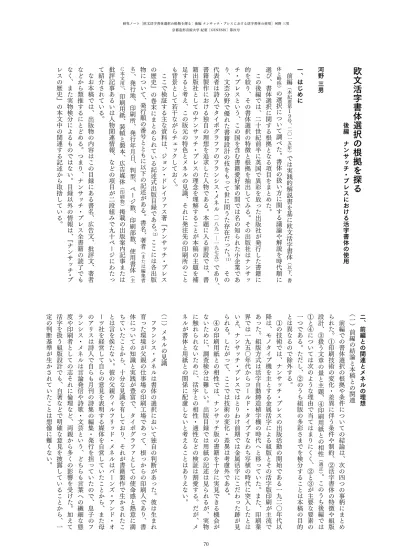
欧文活字書体選択の根拠を探る
後編 ナンサッチ・プレスにおける活字書体の使用 河野 三男 一、はじめに 前 編 ︵ 本 紀 要 第 1 9 号 、 二 〇 一 五 年 ︶ で は 実 践 的 解 説 書 を 基 に 欧 文 活 字 書 体 ︵ 以 下 、 書 体 と 略 称 ︶ の 選 択 に つ い て 調 べ た 。 書 体 の 扱 い 方 に 関 す る 議 論 や 解 説 を 時 代 順 に 選 び 、 書 体 選 択 に 関 す る 根 拠 と な る 項 目 を ま と め た 。 こ の 後 編 で は 、 二 十 世 紀 前 半 に 英 国 で 異 彩 を 放 っ た 出 版 社 が 発 行 し た 書 籍 に 的 を 絞 り 、 そ の 書 体 選 択 の 特 徴 と 根 拠 を 抽 出 し て み る 。 そ の 出 版 社 は ナ ン サ ッ チ ・ プ レ ス と い う 、 こ の 国 を 含 む 書 籍 愛 好 家 の 間 で は 名 の 知 ら れ た 小 企 業 で あ り 、 文 芸 分 野 で 優 れ た 書 籍 設 計 の 技 を も っ て 世 に 問 う た 存 在 だ っ た 。 (1) そ の 代 表 者 は 詩 人 で タ イ ポ グ ラ フ ァ の フ ラ ン シ ス ・ メ ネ ル ︵ 一 八 九 一 ︱ 一 九 七 五 ︶ で あ り 、 書 籍 製 作 に お け る 独 自 の 理 想 を 追 求 し た 人 物 で あ る 。 本 題 に 入 る 前 段 で は 、 書 籍 出 版 社 と し て の ナ ン サ ッ チ ・ プ レ ス の 理 念 を 理 解 す る こ と が 本 稿 の 主 題 を 補 足 す る と 考 え 、 こ の 版 元 の 特 色 と メ ネ ル の 見 識 、 そ れ に 発 注 先 の 印 刷 所 の こ と も 背 景 と し て 若 干 な が ら チ ェ ッ ク し て お く 。 こ こ で 検 証 す る 主 な 資 料 は 、 ジ ョ ン ・ ド レ イ フ ァ ス 著 ﹃ ナ ン サ ッ チ ・ プ レ ス の 歴 史 ﹄ の 巻 末 に ま と め ら れ て い る 記 述 式 出 版 目 録 で あ る 。 (2)こ こ に は 各 出 版 物 に つ い て 、 発 行 順 の 番 号 と と も に 以 下 の 記 述 が あ る 。 書 名 、 著 者 ︵ ま た は 編 集 者 名 ︶ 、 発 行 地 、 印 刷 所 、 発 行 年 月 日 、 判 型 、 ペ ー ジ 数 、 印 刷 部 数 、 使 用 書 体 ︵ 主 に 本 文 用 ︶ 、 印 刷 用 紙 、 装 幀 と 製 本 、 広 告 媒 体 ︵ 印 刷 物 ︶ 掲 載 の 出 版 案 内 記 事 ま た は 批 評 記 事 あ る い は 人 物 関 連 情 報 、 な ど の 項 目 が 二 段 組 み で 九 十 ペ ー ジ に わ た っ て 紹 介 さ れ て い る 。 な お 本 稿 で は 、 出 版 物 の 内 容 は こ の 目 録 に あ る 書 名 、 広 告 文 、 批 評 文 、 著 者 な ど か ら 類 推 す る に と ど め る 。 つ ま り 、 ナ ン サ ッ チ ・ プ レ ス 全 書 籍 の 読 了 で も な く 、 ま た 実 物 検 分 に よ る も の で は な い 。 目 録 以 外 の 情 報 は 、﹃ ナ ン サ ッ チ ・ プ レ ス の 歴 史 ﹄ の 本 文 中 の 関 連 す る 記 述 か ら 取 捨 し て い る 。 二、前編との関連とメネルの理想 ︵ 一 ︶ 前 編 の 結 論 と 本 稿 と の 関 連 前 編 で の 書 体 選 択 の 根 拠 や 条 件 に つ い て の 結 論 は 、 次 の 四 つ の 事 柄 に ま と め ら れ た 。 ① 印 刷 技 術 の 変 化 ・ 差 異 に 伴 う 条 件 や 制 約 、 ② 活 字 書 体 の 特 徴 や 組 版 設 計 、 ③ 扱 う 文 章 の 量 と 主 題 、 ④ 印 刷 用 紙 と の 相 性 ︵ 適 正 ︶ 。 こ の う ち 後 編 で は ① と ④ に つ い て は 次 の よ う な 理 由 で 当 て は ま り に く く 、 ② と ③ が 主 要 な 要 素 の 一 つ で あ る 。 た だ し 、 ② の う ち 組 版 の 多 彩 さ ま で を 検 分 す る こ と は 本 稿 の 目 的 と は 異 な る の で 除 外 す る 。 ① の 技 術 で は 、 ナ ン サ ッ チ ・ プ レ ス の 出 版 活 動 の 開 始 で あ る 一 九 二 〇 年 代 以 降 は 、 モ ノ タ イ プ 機 を 主 と す る 金 属 活 字 に よ る 組 版 と そ の 活 字 版 印 刷 が 主 流 で あ っ た 。 組 版 方 式 は 活 字 自 動 鋳 造 植 字 機 の 時 代 へ と 移 っ て い た 。 ま た 、 印 刷 業 界 で は 一 九 五 〇 年 代 か ら コ ー ル ド ・ タ イ プ す な わ ち 写 植 の 時 代 に 突 入 し た と は い え 、 ナ ン サ ッ チ ・ プ レ ス で は と り わ け 前 期 で は 金 属 活 字 に こ だ わ っ た 跡 が 見 ら れ る 。 し た が っ て 、 こ こ で は 技 術 の 変 化 ・ 差 異 は 考 慮 外 で あ る 。 ④ の 印 刷 用 紙 と の 相 性 で は 、 ナ ン サ ッ チ 版 の 書 籍 を 十 分 に 実 見 で き る 機 会 が な い た め に 、 調 査 検 分 は 難 し い 。 出 版 目 録 で は 用 紙 の 記 述 は 見 ら れ る が 、 実 物 に 触 れ ら れ な い た め に 、 活 字 と の 相 性 ・ 適 性 な ど の 検 証 は 割 愛 す る 。 だ が 、 メ ネ ル が 書 体 と 用 紙 と の 関 係 に 配 慮 し な い と 考 え る こ と は あ り え な い 。 ︵ 二 ︶ メ ネ ル の 見 識 フ ラ ン シ ス ・ メ ネ ル は 書 体 の 選 択 に お い て 独 自 の 判 断 が あ っ た 。 彼 は 生 ま れ 育 っ た 環 境 が 父 親 の 仕 事 場 の 印 刷 工 場 で あ っ て 、 根 っ か ら の 印 刷 人 で あ り 、 書 体 に つ い て の 知 識 と 実 践 が 豊 富 で 、 タ イ ポ グ ラ フ ァ と し て の 使 命 感 と 熱 意 に 満 ち て い た こ と か ら 、 十 分 な 見 識 を 有 し て お り 、 そ れ が 書 籍 製 作 で 生 か さ れ た こ と は 言 を 俟 た な い 。 彼 の 父 親 ウ ィ ル フ リ ッ ド ・ メ ネ ル は バ ー ン ズ ・ ア ン ド ・ オ ー ツ 社 を 経 営 し て 自 ら の 意 見 を 表 明 す る 媒 体 を 自 営 し て い た こ と か ら 、 ま た 母 の ア リ ス は 詩 人 で 自 ら も 月 刊 の 詩 集 の 編 集 ・ 発 行 を 担 っ て い た の で 、 息 子 の フ ラ ン シ ス ・ メ ネ ル は 言 論 発 信 や 詩 歌 ・ 文 芸 と い う 、 ど ち ら も 言 葉 へ の 繊 細 な 態 度 や 印 刷 者 と し て の 志 そ れ に 倫 理 な ど 、 両 親 か ら 多 く の 影 響 を 受 け た 。 加 え て 活 字 を 扱 う 組 版 設 計 で も 、 自 著 な ど で 明 確 な 意 見 を 披 露 し て い る こ と か ら 、 一 定 の 判 断 基 準 が 生 か さ れ て い た こ と は 想 像 に 難 く な い 。示 し て 、 そ れ を 読 み 手 と 共 有 ・ 共 感 し た り 気 づ か せ た り す る 工 夫 で あ る 。 そ こ に こ そ 装 飾 の 意 図 が あ る 、 と メ ネ ル は 考 え て い た 。 そ の 意 味 で 装 飾 は 、 書 き 手 の 意 図 を 妨 げ な い 程 度 に 何 か を 付 加 す る あ る い は 増 幅 す る と い う ﹁ 創 造 的 機 能 性 ﹂ と も 呼 ぶ べ き 配 慮 を 期 待 さ れ て い る 素 材 で も あ っ た 。 読 者 が 模 様 や 図 柄 を 目 に し て 、 紙 面 に 独 特 な 印 象 深 い 表 情 や 心 理 的 な 立 体 感 を 与 え ら れ る 楽 し み と で も 言 え よ う 。 こ の 種 の オ ー ナ メ ン ト 類 の 扱 い 方 に は 組 版 技 術 や 創 造 力 が 必 要 と さ れ 、 そ の パ タ ー ン を 選 ん だ 根 拠 も 試 さ れ る 。 花 形 装 飾 活 字 な ど は 、 そ の 意 味 で タ イ ポ グ ラ フ ァ に と っ て の 腕 の 見 せ ど こ ろ で あ り 、 創 造 性 を か き 立 て ら れ る 素 材 で あ る は ず だ 。 他 方 で ド レ イ フ ァ ス は 、 メ ネ ル が 一 九 二 三 年 に 発 行 し た 活 字 見 本 帳 の 奥 書 か ら 以 下 の よ う な 文 章 を 引 用 し て い る 。 (5) あ る べ き 活 字 と は 、 次 の よ う に 常 識 以 前 の こ と で あ る 。 ① 何 は さ て お き 、 読 み や す い こ と 。 ② 確 か め う る 規 範 、 美 、 ま た は ︵ そ し て ︶ 伝 統 に 従 う こ と 。 ③ で き る だ け 明 瞭 で あ る こ と 。 ④ 印 刷 さ れ た 言 葉 の 意 味 に 対 し て 、 ︵ 活 字 の ︶ 特 色 が ふ さ わ し い こ と 。 ⑤ 飾 り 罫 や 図 版 と 調 和 す る ﹁ 濃 淡 ﹂ で あ る こ と 。 ⑥ 決 め ら れ た 印 刷 工 程 と 決 め ら れ た 紙 に よ っ て 効 果 の あ る 再 生 が 可 能 な こ と 。 ⑦ ︵ 常 識 的 な 心 理 学 の 言 葉 を 使 う と ︶ 読 者 の 心 の 中 で 正 し い 連 想 を 確 立 す る こ と 。 こ こ に メ ネ ル の 書 籍 製 作 に か け る 熱 く か つ 冷 静 な 姿 勢 の 均 衡 の 程 が 十 分 に う か が え る 。 ナ ン サ ッ チ 版 の 書 籍 の 全 て が こ の よ う な 理 想 を 具 現 し て い る か ど う か は 定 か で は な い が 、 少 な く と も そ の 意 気 込 み と 質 の 維 持 に 懸 命 で あ っ た と 想 像 で き る 。 同 社 の 設 立 に 際 し て ﹁ 中 身 の 重 要 性 、 体 裁 の 美 し さ 、 適 正 な 定 価 と い う 三 つ の 理 想 に 従 っ て 中 身 を 選 ん で 製 作 す る こ と に あ る ﹂ と い う 確 固 た る 意 志 が 、 一 九 二 三 年 の 設 立 直 後 の 出 版 案 内 の 中 で 表 明 さ れ て い る 。 (6) な お 、 日 本 で は こ の 時 期 に す で に 一 人 の 詩 人 が ナ ン サ ッ チ ・ プ レ ス に 注 目 し て い た 。﹃ 游 牧 記 ﹄ を 残 し た 夭 折 の 詩 人 ・ 平 井 功 が メ ネ ル に 手 紙 を 送 り 、 そ の 書 籍 製 作 に つ い て 質 問 し て い た と 聞 い て い る 。 日 夏 耿 之 介 や 庄 司 泉 水 ら の 愛 書 家 彼 に よ る 書 籍 製 作 に 対 す る 態 度 は 、 そ の 著 ﹃ イ ギ リ ス の 印 刷 本 ﹄ (3)と ジ ョ ン ・ ド レ イ フ ァ ス 著 ﹃ ナ ン サ ッ チ ・ プ レ ス の 歴 史 ﹄ (4)に 詳 し い 。 以 下 の 彼 の 言 葉 か ら そ の 真 摯 な 姿 勢 や 理 想 と す る 実 践 方 針 を 見 て み る 。 ﹁ 可 読 性 と は 、 十 分 に 油 が 注 が れ た ベ ア リ ン グ の こ と で 、 意 味 と い う 車 輪 を ギ ー ギ ー と 音 を 立 て ず に 回 転 さ せ る も の だ ﹂ ﹁ 言 葉 に つ い て の 様 々 な 表 し 方 が 可 能 な 限 り あ る 。著 者 の 言 葉 を 肉 体 化 す る こ と だ ﹂ ﹁ 書 物 の 物 理 的 な 心 臓 や 頭 部 は 、 印 刷 さ れ た ペ ー ジ に あ る ﹂ ﹁ 我 々 の 役 に 立 ち 、 我 々 を 救 う の は 、 活 字 で あ る ﹂ ﹁ ︵ 新 聞 の ︶ 印 刷 は 偉 大 な 記 録 者 だ 。 書 類 は 残 り 続 け 、 そ の 証 拠 は い つ で も 入 手 で き て 、 記 事 は 歴 史 と な る 。 証 拠 を 隠 す こ と は 難 し い し 、 印 刷 は 究 極 の 言 葉 を 有 す る こ と に 至 る 。 つ ま り 鉛 で で き た 二 十 六 の 兵 士 で 、 私 は 世 界 を 征 服 し た と ﹂ ﹁ 書 物 は 分 か り や す く あ る べ き で 、 書 き 手 の 目 的 へ の 誠 実 な 奉 仕 で あ る ﹂ ﹁ 書 物 は 読 ま れ る だ け の も の で は な く 、 尊 重 ・ 評 価 さ れ る べ き で も あ る 。 言 い 換 え れ ば 、 書 物 は 分 か り や す く あ る べ き で 、 書 き 手 の 目 的 ・ 意 図 へ の 誠 実 な 奉 仕 で あ る 。 ま た 、 読 み や す い こ と が 必 要 だ 。 時 と し て 書 き 手 の 意 図 を 増 幅 し た り 、 あ る い は そ れ 自 体 の 不 可 欠 な 形 態 へ と 接 近 す る な ど だ ﹂ ﹁ さ さ や か な が ら も 印 刷 と い う 男 勝 り の 三 つ の 女 神 を 眺 め て み よ う 。そ れ は 分 か り や す さ 、 読 み や す さ 、 そ し て 装 飾 だ ﹂ ﹁ 理 想 を 言 え ば 、 文 章 の 一 行 は 八 か ら 十 一 単 語 で あ る べ き だ ろ う ﹂ ﹁ 派 手 に 着 飾 っ た 書 物 で は な く 、 絶 妙 に し て 的 確 に 、 出 し ゃ ば る こ と な く 書 物 へ の 思 い で 身 を ま と っ た 書 物 を 欲 し て い る の だ ﹂ こ こ に 引 用 し た ﹁ 男 勝 り の 女 神 ﹂ の 三 番 目 の 装 飾 は 、 ナ ン サ ッ チ ・ プ レ ス の 特 徴 の 一 つ で あ る ﹁ 隠 喩 に 富 ん だ 印 刷 (a llu siv e p rin tin g) ﹂ を 理 解 す る に は 好 例 で あ る 。 こ の 言 葉 は メ ネ ル が 尊 敬 す る ア メ リ カ 人 ブ ル ー ス ・ ロ ジ ャ ー ズ ︵ 一 八 七 〇 ︱ 一 九 五 七 ︶ が 既 に 唱 え て い た 。 こ の 隠 喩 と は 書 籍 製 作 全 般 の デ ザ イ ン つ ま り 装 幀 、 製 本 材 料 、 扉 な ど と 、 書 体 選 択 で も 発 揮 さ れ る 。 例 え ば 装 飾 と は た だ 眼 を ひ く も の で も や た ら に 飾 り 立 て る こ と で も な く 、 メ ッ セ ー ジ の 内 容 や 背 景 を 暗
で き る 記 述 が あ り 、 ナ ン サ ッ チ 社 内 で 印 刷 さ れ た か 同 族 関 係 の 印 刷 工 場 に よ る も の と 思 わ れ る が 特 定 で き ず 、 実 態 が 曖 昧 で あ る と い う 理 由 に よ る 。 業 者 名 の 内 訳 は 、 ウ ィ リ ア ム ・ ブ レ ド ン ・ ア ン ド ・ サ ン 社 が 二 十 二 点 、 R ・ R ク ラ ー ク 社 が 十 九 点 、 ウ ィ リ ア ム ・ ク ロ ウ ズ ・ ア ン ド ・ サ ン ズ 社 が 十 四 点 、 ロ バ ー ト ・ マ ク レ ホ ウ ズ 社 が 十 三 点 、 キ ー ノ ッ ク ・ プ レ ス が 十 二 点 、 オ ッ ク ス フ ォ ー ド 大 学 印 刷 局 が 十 一 点 、 ケ ン ブ リ ッ ジ 大 学 印 刷 局 と フ ァ ン フ ェ ア ・ プ レ ス が 各 十 点 、 ヘ リ テ ィ ッ ジ ・ プ レ ス と 私 的 印 刷 所 が 各 九 点 で あ る 。 海 外 発 注 は ア メ リ カ と フ ラ ン ス に あ り 、 前 者 は ヘ リ テ ィ ッ ジ ・ プ レ ス と 、 ク ィ ン ・ ア ン ド ・ ボ ー デ ン 社 、 レ オ ・ ハ ー ト 社 で 、 後 者 は プ ロ タ 印 刷 社 で あ る 。 次 に こ れ ら の 印 刷 所 が 受 注 し た 書 体 の 特 徴 を 眺 め て み る 。ウ ィ リ ア ム ・ ブ レ ド ン ・ ア ン ド ・ サ ン 社 は キ ャ ズ ロ ン 書 体 と プ ラ ン タ ン 書 体 で の 組 版 と 印 刷 を 主 に 受 注 し て お り 、 そ の 他 に 四 書 体 の 使 用 が 記 録 さ れ て い る R ・ R ク ラ ー ク 社 は ス コ ッ チ ・ ロ ー マ ン 書 体 と バ ス カ ヴ ィ ル 書 体 そ れ に タ イ ム ズ ・ N ・ R 書 体 の 使 用 が 多 い 。 ウ ィ リ ア ム ・ ク ロ ウ ズ ・ ア ン ド ・ サ ン ズ 社 は モ ノ タ イ プ 社 と 関 係 が 強 く 、 メ ネ ル か ら 七 書 体 の 仕 事 を 受 注 し 、 ナ ン サ ッ チ 版 プ ラ ン タ ン 書 体 と い う 特 注 書 体 の 使 用 が 四 点 あ る 。 ロ バ ー ト ・ マ ク レ ホ ウ ズ 社 は 七 書 体 を 指 定 さ れ 、 タ イ ム ズ ・ N ・ R 書 体 が も っ と も 多 い 。 キ ー ノ ッ ク ・ プ レ ス は 六 書 体 で の 印 刷 を 受 注 し 、 モ ノ タ イ プ 社 版 ギ ャ ラ モ ン 書 体 ︵ ジ ャ ノ ン 系 で 、 ギ ャ ラ モ ン 書 体 の 模 倣 の 復 刻 版 ︶ と ベ ン ボ 書 体 で の 組 版 受 注 が 際 立 つ 。 オ ッ ク ス フ ォ ー ド 大 学 印 刷 局 は 十 一 点 で 三 書 体 の 使 用 を 受 注 し 、 そ の 内 で 同 印 刷 局 が 歴 史 的 遺 産 と し て 所 有 す る 十 七 世 紀 前 半 の フ ェ ル 書 体 の 母 型 か ら 鋳 込 ん だ 活 字 を 七 点 で 使 用 し た 。 ケ ン ブ リ ッ ジ 大 学 印 刷 局 は 九 書 体 で 十 点 を 印 刷 し て い る し 、 フ ァ ン フ ェ ア ・ プ レ ス に は 特 徴 あ る 書 体 は み ら れ な い が 、 ガ ウ デ ィ ・ モ ダ ン 書 体 が 目 を 引 く 。 ア メ リ カ の 印 刷 所 で あ る ヘ リ テ ィ ッ ジ ・ プ レ ス は 特 に 多 く 使 用 し て い る 書 体 は な く 八 書 体 で あ る が 、 一 書 体 で 明 記 が な い 。 私 的 印 刷 所 は ジ ャ ン ソ ン 書 体 で 半 分 の 四 点 を 印 刷 し て い る 。 フ ラ ン ス の プ ロ タ 社 で は コ シ ャ ン と フ ー ル ニ エ の 二 書 体 で の 印 刷 を 受 注 し 、 ク ィ ン ・ ア ン ド ・ ボ ー デ ン 社 と レ オ ・ ハ ー ト 社 で 合 わ せ て 四 点 を 印 刷 し 、 全 て コ シ ャ ン 書 体 で 印 刷 し て い る 。 両 書 体 は フ ラ ン ス 生 ま れ で 、 そ の 復 刻 版 活 字 で あ る 。 こ れ ら 以 外 で 我 々 に 馴 染 み の あ る 印 刷 所 を あ げ て お く 。 オ リ ヴ ァ ・ サ イ モ ン が 携 わ っ て い た カ ー ウ ェ ン ・ プ レ ス 、 オ ラ ン ダ の ハ ー グ に あ っ た ヨ ハ ネ ス ・ エ た ち が 平 井 に ナ ン サ ッ チ 版 の 魅 力 に つ い て 教 え た と み ら れ る 。 平 井 に は 組 版 へ の 意 欲 的 な 挑 戦 に 応 え う る 印 刷 所 の 選 択 な ど に 関 し て 、 困 難 や 悩 み が あ っ た か ら と 伝 え ら れ て い る 。 そ し て ド レ イ フ ァ ス は 活 字 の 機 能 に 関 す る 、 次 の よ う な メ ネ ル の 言 及 を 紹 介 し て い る 。 文 字 の プ ロ ポ ー シ ョ ン に お い て 美 し さ に ﹁ 純 粋 な ﹂ 基 準 と い う も の が あ る と い う 考 え に 傾 い た が 、 そ の 種 の 美 し さ の 代 わ り と な る 最 も 有 効 で 実 証 で き る も の が あ る 場 合 に は 、 殊 の 外 難 し く て 疑 い が あ る こ と に 四 苦 八 苦 す る 必 要 は な い 。 こ れ は 用 の 美 ︵ bea uty of util ity ︶ と い う 見 解 で あ っ て 、伝 統 と 慣 習 へ の 尊 重 で も あ る 。 ︵ 略 ︶ 印 圧 の 鋭 さ ・ 明 快 さ 、 曲 線 と 結 合 部 、 極 微 で の 正 確 さ と 安 定 感 、 目 の 歪 み ︵ 人 の 目 は 実 測 上 の 中 央 を 下 に 見 る し 、 こ れ は 知 ら れ て い る ︶ へ の 考 慮 、 文 字 が 満 足 の ゆ く よ う に つ な が り 、 語 を 形 成 し 、 文 字 が 示 さ れ た と き の 媒 体 の た め の 感 覚 ︱ ︱ 金 属 、 石 、 イ ン ク ︱ ︱ そ れ と そ れ を 作 っ た 道 具 へ の 配 慮 、 あ の 活 字 こ れ ら の す べ て が 技 術 上 の 完 璧 な 現 れ で あ り 、 現 段 階 で 美 の 定 義 で あ る か ど う か の 判 断 の た め の 実 際 上 の 試 し と な る の で あ る 。 (7) ﹁ 用 の 美 ﹂ あ る い は ﹁ 用 と 美 ﹂ と は 、我 が 国 で 柳 宗 悦 が 唱 え た 民 芸 運 動 で の キ ー ワ ー ド の 一 つ で あ る が 、 そ の 契 機 は 十 九 ︱ 二 十 世 紀 の イ ギ リ ス で 起 き た ア ー ツ ・ ア ン ド ・ ク ラ フ ツ 運 動 に あ っ た 。 メ ネ ル も そ の 時 代 の 空 気 を 十 分 に 吸 っ て い た こ と と 無 関 係 で は あ り え な い 。 た だ し 、 工 芸 作 家 W ・ モ リ ス が 辿 り 着 い た 書 籍 製 作 の 態 度 は 、 タ イ ポ グ ラ フ ィ の 理 解 の 深 さ に お い て メ ネ ル に は 及 ば な い 。 書 き 手 へ の 寄 り 添 い 方 や 意 識 が モ リ ス に は 弱 い こ と で そ の 結 果 は ア ー ト に 傾 き 、 逆 に メ ネ ル は 真 の デ ザ イ ン に 没 入 で き た 。 ︵ 三 ︶ 発 注 先 の 印 刷 所 ナ ン サ ッ チ ・ プ レ ス か ら 印 刷 を 受 注 し た 企 業 に つ い て 見 て み る 。 明 記 さ れ て い る 社 名 の 総 計 は 三 十 六 社 ほ ど あ り 、 受 注 し た 点 数 か ら み て 上 位 十 社 だ け で 百 二 十 九 点 を 印 刷 し て い る 。 こ れ は 全 体 の 七 十 % ほ ど に あ た る 。 受 注 印 刷 所 を ﹁ 三 十 六 社 ほ ど ﹂ と し た が 、こ れ は ﹁ 私 的 に 印 刷 ﹂ と い う 自 社 内 で の 作 業 を 推 測
た 事 実 を 報 告 し て い る 。 (8)こ れ は プ ラ ン タ ン 書 体 の こ と を 指 し て い る 。 ま た 、 ラ イ ノ タ イ プ 社 版 の バ ス カ ヴ ィ ル 、 ス コ ッ チ ・ ロ ー マ ン 、 グ ラ ン ジ ョ ン 、 ギ ャ ラ モ ン な ど の 一 部 の 書 体 や 、 手 組 み 用 の ジ ャ ン ソ ン な ど も 選 ば れ て い る 。 と り わ け ジ ャ ン ソ ン 書 体 は 十 二 点 で 使 用 さ れ 、 そ の う ち 手 組 み 用 七 点 、 ラ イ ノ タ イ プ 社 版 が 三 点 、 不 明 が 二 点 と 、 手 組 み 用 に ナ ン サ ッ チ 版 と し て 修 正 文 字 種 を 含 む 書 体 が 使 用 さ れ て い る 。 ︵ 二 ︶ 使 用 書 体 の 数 メ ネ ル お よ び 彼 の 後 継 者 が 書 籍 な ら び に 小 冊 子 で 選 ん だ 本 文 用 書 体 の 一 覧 は 表 1 に 示 す 通 り で あ る 。 全 発 行 書 名 数 一 九 四 で 、 記 載 不 明 を 含 め て 三 十 一 種 類 の 書 体 が 使 用 さ れ た が 、 書 名 数 は 一 四 二 点 で 、 シ リ ー ズ で あ る が 異 な る 内 容 で あ れ ば 一 点 と 数 え た 。同 一 書 名 で 複 数 書 体 の 混 植 と 書 体 名 の 不 明 が あ る た め に 、書 名 数 よ り も 多 く な っ て い る 。 主 要 選 択 書 体 に つ い て は 、 上 位 十 書 体 で 百 三 十 二 点 を 組 ん で お り 、 そ の 割 合 は 六 十 八 % で 七 割 近 い 。 ち な み に 上 位 五 位 ま で の 六 書 体 で 、 全 体 の 五 割 を 超 え て い る 。 こ の 場 合 、 本 稿 の 基 に な る 文 献 で あ る ド レ イ フ ァ ス 著 ﹃ ナ ン サ ッ チ ・ プ レ ス の 歴 史 ﹄ も 同 じ ナ ン サ ッ チ 発 行 で あ る が 、 そ こ に 使 用 さ れ て い る 活 字 の バ ル ブ 書 体 は こ の リ ス ト か ら 除 外 し て い る 。 ま た 、 表 一 の 使 用 書 体 の う ち 使 用 開 始 年 と 活 字 製 造 年 に 注 目 す る と 、 興 味 あ る こ と が 見 ら れ る 。 バ ル マ ー 書 体 は 製 造 と 同 年 に 、 ギ ャ ラ モ ン 書 体 と グ ラ ン ジ ョ ン 書 体 は 翌 年 に 、 バ ス カ ヴ ィ ル 書 体 と ベ ン ボ 書 体 と ガ ウ デ ィ 書 体 は 二 年 後 に 、 そ れ ぞ れ 使 用 さ れ て い る 。 メ ネ ル が い か に 新 し い 書 体 の 出 現 に 敏 感 だ っ た か を 物 語 る 。 こ れ ら か ら ラ イ ノ タ イ プ 版 グ ラ ン ジ ョ ン 書 体 を 除 く 五 書 体 は 、 全 て モ ノ タ イ プ 社 版 で あ る 。 ち な み に 製 造 後 三 年 で の 使 用 は ポ リ フ ィ ラ ス 書 体 と そ の イ タ リ ッ ク 体 の 別 名 ブ ラ ド ー 書 体 で あ る 。 ン ス ヘ デ 社 、 キ ャ ズ ロ ン 書 体 を 復 活 さ せ た ウ ィ テ ィ ン ガ ム 運 営 の チ ジ ッ ク ︵ チ ズ ウ ィ ッ ク ︶ ・ プ レ ス な ど が あ る 。 活 字 書 体 と そ の 組 版 の 要 望 に 応 え う る 印 刷 所 が 指 定 さ れ て い た と 考 え ら れ る こ と か ら 、 希 望 書 体 を 備 え て い る 印 刷 所 を 選 ん で の 発 注 だ ろ う 。 本 文 の 組 版 と 印 刷 を 分 け て 発 注 し た こ と も あ る の で 、 印 刷 所 が 全 て 先 に あ げ た 書 体 を 備 え て 組 ん で い た の で は な い こ と に 留 意 が 必 要 で あ る が 、 そ の 方 法 は こ こ で は 省 く 。 ナ ン サ ッ チ ・ プ レ ス は 出 版 業 社 で あ り 、 メ ネ ル は 主 に 編 集 と デ ザ イ ン を 担 当 し て い た 。 彼 が 活 躍 し た 期 間 は 第 二 次 大 戦 の 前 ま で で 、 そ の 後 は ア メ リ カ 人 に 経 営 が 委 ね ら れ た 。 そ の 歴 史 の 前 半 の 運 営 と 書 籍 製 作 の 主 体 は メ ネ ル で あ り 、 そ の 意 志 は 助 言 な ど で そ の 後 の 経 営 陣 に 継 続 さ れ た と は い え 、 実 際 の 書 籍 デ ザ イ ン は 変 わ ら ざ る を 得 な か っ た だ ろ う 。 そ れ に し て も 、 ナ ン サ ッ チ と い う 名 称 を 普 及 さ せ た 功 績 は メ ネ ル の デ ザ イ ン 的 感 性 と 文 学 お よ び タ イ ポ グ ラ フ ィ の 才 能 ・ 知 識 に あ る こ と は 疑 い な い 。 さ ら に 人 的 交 流 の 広 さ も あ り 、 そ の 条 件 か ら 生 み 出 さ れ た 書 籍 の 外 部 と 内 部 の 質 の 高 さ や 豊 か さ は 、 並 び の な い 光 彩 を 放 っ て 人 気 を 得 て い る 。 以 上 の こ と を 念 頭 に 、 次 に ナ ン サ ッ チ ・ プ レ ス の 書 体 使 用 状 況 の 全 体 像 を 概 観 し て み る 。 三、使用書体の特徴と概略 ︵ 一 ︶ 活 字 の 供 給 ナ ン サ ッ チ が 書 籍 本 文 の 組 版 ・ 印 刷 を 外 注 し た 時 代 は 、 二 十 世 紀 前 半 の 半 世 紀 ほ ど ︵ 一 九 二 三 ︱ 一 九 六 八 年 ︶ の 期 間 で あ る 。 そ れ は モ ノ タ イ プ 式 と ラ イ ノ タ イ プ 式 の 自 動 鋳 造 植 字 機 に よ る 金 属 活 字 で の 機 械 組 版 が 全 盛 を 誇 っ て い た 時 代 で あ る 。 さ ら に 、 ナ ン サ ッ チ が 選 択 し た 書 体 は ス タ ン リ ー ・ モ リ ス ン ︵ 一 八 八 九 ︱ 一 九 六 七 ︶ と の 関 係 を 無 視 で き な い 。 モ リ ス ン は メ ネ ル の 若 い 頃 か ら の 友 人 で あ り 、 当 時 モ ノ タ イ プ 社 で 活 字 書 体 復 刻 計 画 の 指 揮 を 執 っ て い た 。 メ ネ ル が 選 ん だ 書 体 の 大 多 数 が モ ノ タ イ プ 社 製 の 活 字 で あ っ た こ と か ら 、 相 互 の 理 解 と 友 情 が 友 好 裏 に 働 い た こ と が 伝 わ っ て い る 。 例 え ば ジ ョ ン ・ ド レ イ フ ァ ス は ﹁ モ リ ス ン の 存 在 に よ り ラ ン ス ト ン ・ モ ノ タ イ プ 社 か ら ︵ ナ ン サ ッ チ へ ︱ 引 用 者 ︶ の 特 殊 な 文 字 種 の 調 達 が 容 易 に な っ た ﹂ と し て 、 下 図 に 見 ら れ る よ う に 大 文 字 を 低 く さ せ た り ア セ ン ダ ー や デ ィ セ ン ダ ー を 長 く さ せ た り す る な ど の 工 夫 が 要 請 さ れ プランタン書体の比較: 同じ文字で左がナンサッチ版、右がモノタイプ版。
順位 書体名 使用数 割合(%) 使用期間(年) 活字製造年* MT外の製造 供給所名 製造所(MT) 1 キャズロン(Caslon) 26 13.40 1923 – 38 1916 (13) ? (13) 2 プランタン(Plantin) 19 9.79 1923 – 55 1913 (19) 3 ギャラモン(Garamond) 16 8.25 1923 – 53 1922 (10) 1924 (2) LT 1917 (4) ATF
4 タイムズ(Times New Roman.) 15 7.73 1939 – 53 1932 (13) 1932 (2) LT?
5 バスカヴィル(Baskerville) 12 6.19 1925 – 39 1923 (10) 1923 (2) LT ジャンソン(Janson) 12 6.19 1926 – 39 1937 (3) LT 1919 (9) Stempel 6 スコッチ・ローマン(Scotch R.) 10 5.15 1925 – 35 1920 (8) ? (2) ? 7 コシャン(Cochin) 8 4.12 1931 – 44 1923 (8) 8 ベンボ(Bembo) 7 3.61 1931 – 64 1929 (7) フェル(Fell) 7 3.61 1923 – 37 1672 (7) OUP 小 計 132 68.04 88 44 9 ボドニ(Bodoni) 6 3.09 1926 – 36 1922 (5) ? (1) ? 10 エアハルト(Ehrhardt) 5 2.58 1950 – 68 1937 (5) フールニエ(Fournier) 5 2.58 1929 – 63 1925 (5) パペチュア(Perpetua) 5 2.58 1936 – 51 1929 (5) 11 ガウディ・モダン(Goudy Mod.) 4 2.06 1930 – 53 1928 (4) ポリフィラス(Poliphilus) 4 2.06 1926 – 33 1923 (2) ? (2) ?
12 ブラド(Blado = Poliphilus italic) 3 1.54 1926 – 28 1923 (2) ? (1) ?
グランジョン(Granjon) 3 1.54 1932 – 39 1928–31 (3) LT インプリント(Imprint) 3 1.54 1932 – 56 1912 (3) ワルバウム(Walbaum) 3 1.54 1926 – 39 1933 (1) 1919 (2) Berthold 13 バルマー(Bulmer) 2 1.03 1937 – 45 1937 (1) 1928 (1) ATF セントール(Centaur) 2 1.03 1934 – 56 1929 (1) 1929 (1) LT ダンテ(Dante) 2 1.03 1965 – 68 1957 (2) フライシュマン(Fleischmann) 2 1.03 1928 – 34 1929 (2) Enschede 14 ベル(Bell) 1 0.52 1936 1930 (1)
アリギ(Arrighi = Centaur italic) 1 0.52 1934 1929 (1)
カレドニア(Caledonia) 1 0.52 1945 1938 (1) ルテシャ(Lutetia) 1 0.52 1934 1925 (1) Enschede ノイラント(Neuland) 1 0.52 1924 1923 (1) K'spore ロムルス(Romulus) 1 0.52 1954 1931 (1) Enschede ファン・ダイク(Van Dijck) 1 0.52 1928 1935 (1) 小 計 56 28.87 40 16 不明書体 6 3.09 6 鋳造所別小計 128 66 30書体の使用合計数 194 100.00 表 1: 本文主要書体の一覧 * ()内は使用数。特に明記ない場合は、MT(モノタイプ社)を表す。 ** LTはライノタイプ社、AF Tはアメリカ活字鋳造会社、BTはベルトルド社、Sはシュテンペル社、Bはバウアー社。 活字製造年は製造完了年か発売年かにより、1年程度の差異がある。
キャズロン、Caslon プランタン、MT Plantin ギャラモン、MT Garamond コシャン、Cochin ジャンソン、Stempel Janson スコッチ・ローマン、Scotch Roman
タイムズ・ニュー・ローマン、MT Times New Roman フェル、Oxford Fell
バスカヴィル、MT Baskerville ベンボ、MT Bembo
︵ 三 ︶ 使 用 書 体 の 傾 向 ︱ 著 者 ・ ジ ャ ン ル と の 関 連 以 下 で は 発 行 書 籍 全 体 の 七 割 近 く を 占 め る 上 位 十 書 体 に つ い て 、 表 2 と 表 3 を 基 に 探 る 。 表 2 は 著 者 の 生 没 年 代 と ジ ャ ン ル と の 関 連 、 表 3 は 著 者 に つ い て の 判 明 し う る 専 門 分 野 と 特 徴 を 、 そ れ ぞ れ 書 体 別 に ま と め た 。 そ こ か ら 以 下 の 項 目 に つ い て 書 体 選 択 の 傾 向 を 探 る 。 ① 著 者 の 生 没 年 代 ︵ 表 2 参 照 ︶ 、 ② 著 者 の 専 門 分 野 ・ 特 徴 ︵ 表 3 参 照 ︶ 、 ③ ジ ャ ン ル ︵ 表 2 参 照 ︶ 、 ④ 特 徴 的 傾 向 の ま と め 、 の 四 項 目 で あ る 。 な お 、 ジ ャ ン ル に つ い て は カ タ ロ グ 解 説 文 と 書 名 を 参 考 に し つ つ 、 さ ら に 筆 者 が 可 能 な 限 り 調 べ て 判 断 し た 。 個 々 の 内 容 の 背 景 と な る 年 代 に 関 し て こ の カ タ ロ グ か ら 判 断 す る こ と は 、 記 述 で 不 明 が あ り 徹 底 し て い な い た め に 不 可 能 で あ る 。 そ の よ う に 年 代 と ジ ャ ン ル で は 不 明 を 含 む 場 合 が あ る の で 、 表 2 で は 別 途 で 不 明 の 欄 を 設 け て 示 し た 。 表2-8: コシャン書体 ジャンル 著者・内容の年代(世紀) 古 代 17-18 18-19 19-20 不 明 計 戯曲/歌謡/詩歌 1 1 小説/物語 1 1 小説(フランス) 1 4 1 6 小計 1 1 1 4 1 8 表2-7: スコッチ・ローマン書体 ジャンル 著者・内容の年代(世紀) 16 17-18 18-19 19-20 不 明 計 戯曲/歌謡/詩歌 1 1 小説/物語 1 1 随筆・小論/評論 1 2 3 2 8 小計 1 1 2 4 2 10 表2-9: ベンボ書体 ジャンル 著者・内容の年代(世紀) 16-17 18-19 19-20 不 明 計 戯曲/歌謡/詩歌 2 2 小説/物語 1 2 3 随筆・小論/評論 2 2 小計 2 1 4 7 表2-10: フェル書体 ジャンル 著者・内容の年代(世紀) 16-17 17-18 不 明 計 戯曲/歌謡/詩歌 2 2 随筆・小論/評論 1 1 宗教/哲学 1 1 2 その他/不明 1 1 2 小計 5 1 1 7 表2-3: ギャラモン書体 ジャンル 著者・内容の年代(世紀) 古 代 16 - 17 18 - 19 19 - 20 不 明 計 戯曲/歌謡/詩歌 1 3 1 5 小説/物語 1 2 3 1 7 宗教/哲学 1 1 2 その他/不明 1 1 2 小計 4 4 2 5 1 16 表2-6: ジャンソン書体 ジャンル 著者・内容の年代(世紀) 17-18 19-20 不 明 計 戯曲/歌謡/詩歌 1 2 2 5 随筆・小論/評論 1 2 1 4 小説/物語 1 1 その他/不明 1 1 2 小計 3 6 3 12 表2-5: バスカヴィル書体 ジャンル 著者・内容の年代(世紀) 16-17 17-18 18-19 19-20 不 明 計 戯曲/歌謡/詩歌 1 1 3 1 6 小説/物語 1 1 2 随筆/評論 1 1 2 4 小計 1 1 4 2 4 12 表2-4: タイムズ・ニュー・ローマン書体 ジャンル 著者・内容の年代(世紀) 17-18 18-19 19-20 不 明 計 戯曲/歌謡/詩歌 1 3 2 6 小説/物語 1 1 2 自然科学 1 1 随筆・小論/評論 1 1 1 2 5 その他/不明 1 1 小計 2 4 5 4 15 表2-1: キャズロン書体 ジャンル 著者・内容の年代(世紀) 古 代 16-17 17-18 18-19 19-20 不 明 計 戯曲/歌謡/詩歌 1 5 1 3 10 小説/物語 1 1 1 1 4 随筆/評論 2 2 4 宗教 1 1 その他/不明 1 3 3 7 小計 1 2 6 5 9 3 26 表2-2: プランタン書体 ジャンル 著者・内容の年代(世紀) 古 代 16-17 18-19 19-20 不 明 計 戯曲/歌謡/詩歌 1 9 10 小説/物語 1 1 2 随筆・小論/評論 1 1 2 宗教 2 2 その他/不明 1 2 3 小計 3 1 1 13 1 19 表2: 書体別、著者とジャンル(使用数上位10書体)
表3-1:キャズロン書体(18−20世紀)
番 号 著者名または書名中の人物名 著者の分野 特 徴
10 ハドスン(W. H. Hadson, 1841︲1922) 植物学者 自然主義
27・45・85 B・ダーウィン(B. Darwin, 1871︲1954) 絵本作家・挿絵画家 児童文学
E・ダーウィン(E. Darwin, 1876︲1961) 絵本作家・挿絵画家 児童文学
36 b ターナー(Walter Turner, 1889︲1946) 詩人・小説家 評論 43・103 ブレイク(W. Blake, 1757︲1827) 詩人・画家 幻想的・浪漫主義 46・88 レイヴァー(J. Laver, 1806︲1872) 小説家 音楽的・絵画的 48 ヴォルテール(Voltaire, 1694︲1778) 小説家・思想家 啓蒙的合理主義 66 ファルクハー(G. Farquhar, ?) 劇作家 喜劇的 67 アリス・メネル(A. Meynell, 1847︲1922) 詩人(フランシスの母親) 易しい言葉遣い 68 ローレンス(D. H. Lawrence, 1885︲1930) 絵本作家 神秘的唯物論 表3-4:タイムズ・N・ローマン書体(18−20世紀) 番 号 著者名または書名中の人物名 著者の分野 特 徴 15g・116 a・b メネル(F. Meynell, 1891︲1975) 詩人・編集者・出版人 社会主義者 94 コウルリッジ(S. T. Colerridge, 1772︲1834) 詩人 浪漫主義 98 コリアー(J. Collier, 1901︲1980) 小説家 悪魔 106 シモンズ(A. J. A. Symons, 1900-1941) 伝記作家 愛書家 フラワー(D. Flower, 1907– ?) 伝記作家 愛書家 メネル(F. Meynell, 1891︲1975) 詩人・編集者・出版人 社会主義者 111 ホイットマン(W. Whitman, 1819︲1892) アメリカの詩人 自由詩・政治的 114 ホワイト(G. White, 1720︲1793) 博物学 流麗な文体 117 バイロン(Byron, 1788︲1824) 詩人 政治的・風刺的 118 シェリー(Shelly, 1792︲1822) 詩人 浪漫派・無神論 表3-5:バスカヴィル書体と関連人物(17−19世紀) 番 号 著者名または書名中の人物名 著者の分野 特 徴 24 ブレイク(W. Blake, 1757–1827) 詩人・画家 幻想的・浪漫主義 26 ペロル(Perrault, 1628–1703) 詩人・小説家 童話も有名 41 コベット(W. Cobbette, 1763–1835) ジャーナリスト 論争家 90 コウルリッジ(S. T. Colerridge, 1772–1834) 詩人 幻想・神秘的・浪漫派 92 モリス(W. Morris, 1834–1896) 工芸作家・印刷者 社会主義者 表3-2:プランタン書体(19−20世紀) 番 号 著者名または書名中の人物名 著者の分野 特 徴 8・30 トラー(E. Toller, 1893︲1939) 劇作家 反ナチ、左翼 15 a-f・123(編集)メネル(F. Meynell, 1891︲1975) 詩人・編集者・出版人 社会主義者
85 B・ダーウィン(Bernard & Darwin, 1871︲1954) 絵本作家・挿絵画家 児童文学
E・ダーウィン(Elenor Darwin, 1876︲1961) 絵本作家・挿絵画家 児童文学
131 スティヴンスン(R. L. Stevenson, 1850︲1894) 詩人・小説家 旅行作家 133 ラング(A. Lang, 1844︲1912) 民俗学者 お伽話の収集 表3: 書体別、著者専門分野・特徴 (表中の番号とは、カタログの書名番号を示す) 表3-3:ギャラモン書体(古代と19−20世紀) 番 号 著者名または書名中の人物名 著者の分野 特 徴 2 メレディス(G. Meredith, 1828︲1909) 小説家・詩人・評論家 メネルの両親の友人 7 アプレイウス(L. Apuleius, 前2世紀) 作家(ギリシャ) 伝奇小説 12 アナクレオン(Anacreon, 前6世紀) 詩人(ギリシャ) 酒と恋・抒情 63 プルターク(Plutarch, 2世紀) 哲学者(ギリシャ) 博識 16・31 ムーア(G. Moore, 1852︲1933) 小説家 自然主義 19 プラトン(Plato, 前4世紀) 哲学者(ギリシャ) 霊魂不滅・イディア論 107 d ハドスン(W. H. Hudson, 1841︲1922) 植物学者 自然主義 115 キャロル(L. Caroll, 1832︲1898) 小説家・数学者 風刺・幻想的 117 a バルザック(H. Balzac, 1799︲1850) 小説家(フランス) リアリズム文学
表3-6:ジャンソン書体(16−20世紀)
番 号 著者名または書名中の人物名 著者の分野 特 徴
36a メネル(F. Meynell, 1891–1975) 詩人・編集者・出版人 社会主義者
44 ハーバート(G. Herbert, 1593–1633) 聖職者・詩人 形而上派
55a メネル(E. Meynell, 1882–1926) 作家・古書店主 フランシスの兄
65 フォンテネル(B. de Fontenell, ) 思想家・啓蒙家 宗教批判
65a, 68a メネル(F. Meynell, 1891–1975) 詩人・編集者・出版人 社会主義者
82 エヴリン(J. Evelyn, 1620–1706) 日記作家 ? 107c ハウズマン(A. Housman, 1859–1936) 詩人・ラテン語学者 古典・ロマン主義 114 a ストーン(I. Stone, 1903–1989) 伝記作家 ? 表3-8:コシャン書体(18−20世紀) 番 号 著者名または書名中の人物名 著者の分野 特 徴 72 ホーマー(J. Homer, 前8世紀) 詩人(ギリシャ) 吟遊詩人 105 コウルリッジ(S. T. Colerridge, 1772–1834) 詩人(ロマン派) 幻想・神秘的 115c ヴォルテール(Voltaire, 1694–1778) 小説家(仏) 風刺・啓蒙合理 115f フランス(A. France, 1844–1924) 小説家(仏) 批評的 115g モーパッサン(G. Mopassant, 1850–1893) 小説家(仏) 自然主義 115h ゾラ(E. Zola, 1840–1902) 小説家(仏) 自然主義・幻想的 表3-9:ベンボ書体(16−20世紀) 番 号 著者名または書名中の人物名 著者の分野 特 徴 73 シドニー(P. Sydney, 1554–1586) 詩人 ソネット形式 107b シェイクスピア(W. Shakespeare, 1564–1616) 劇作家・詩人 警句・名句・新語
117a バルザック(O. Balzac, 1799–1850) 小説家(仏) リアリズム
128 メネル(F. Meynell, 1891–1975) 詩人・編集者・出版人 社会主義者 132 マクドナルド(G. MacDonald, 1824–1905) 児童文学者・詩人 ? 136 ネスビット(E. Nesbit, 1858–1924) 童話作家 ? 表3-10:フェル書体(16−18世紀) 番 号 著者名または書名中の人物名 著者の分野 特 徴 1・6・71・86 ダン(J. Donne, 1572–1631) 詩人 官能的恋愛詩 37 エヴリン(J. Evelyn, 1620–1706) 日記作家 警句・名句・新語 109 ミルトン(J. Milton, 1608–1674) 詩人 宗教的・幻想的 100(編集)オールト(A. Ault, 1880–1950) ポープの研究者 ? 表3-7:スコッチ・ローマン書体と関連人物(18−20世紀) 番 号 著者名または書名中の人物名 著者の分野 特 徴 52 コンラッド(J. Conrad, 1857–1924) 小説家(ポーランド) ? 64 オースティン(J. Austin, 1775–1817) 小説家 写実主義 71a ディケンズ(C. Dickens, 1812–1870) 詩人 諧謔的 75 ハズリット(W. Hazlitt, ?–1930) 詩人・随筆家 浪漫主義 キーンズ(G. Keynes, ?) ? 114b メレコヴスキー(Merejcoveski, 1866–1941) 詩人・小説家(ロシア) 歴史小説
十 六 世 紀 フ ラ ン ス を 代 表 す る 世 界 的 に 有 名 な ギ ャ ラ モ ン 設 計 の 活 字 ま た は そ れ を 模 倣 し た 十 七 世 紀 の 活 字 を モ デ ル に 、 十 九 世 紀 末 か ら 二 十 世 紀 初 頭 に 欧 米 各 国 の 活 字 鋳 造 所 か ら 供 給 さ れ た 。 ① 十 九 ︱ 二 十 世 紀 と 十 六 ︱ 十 七 世 紀 、 そ れ に 古 代 の 著 者 が 目 立 つ 。 ② 九 人 の 著 者 の う ち 、 ギ リ シ ャ 人 四 名 と フ ラ ン ス 人 の 一 名 、 計 五 名 が 外 国 人 著 者 。 古 代 ギ リ シ ャ の 小 説 や 思 想 を 内 容 と す る も の が 目 立 つ が 、 伝 奇 小 説 、 叙 情 的 、 風 刺 的 、 自 然 主 義 、 リ ア リ ズ ム な ど 多 様 な ジ ャ ン ル 。 ③ 小 説 ・ 物 語 と 詩 歌 ・ 韻 文 ・ 戯 曲 に 多 い 。 ④ ギ ャ ラ モ ン 書 体 誕 生 の 世 紀 と の 一 致 が あ る の は 四 点 。 ギ リ シ ャ 時 代 の 著 者 が 多 め で 、 ギ リ シ ャ 時 代 と 十 六 世 紀 と 二 十 世 紀 の ﹁ 著 者 の 年 代 ﹂ そ れ に 多 岐 に わ た る ﹁ ジ ャ ン ル ﹂ が 特 徴 。 ■ タ イ ム ズ ・ ニ ュ ー ・ ロ ー マ ン 書 体 一 九 三 二 年 に 日 刊 新 聞 用 に 特 化 し て 設 計 さ れ た 書 体 。 黒 み が や や 強 く 硬 質 な テ ク ス チ ュ ア を 印 象 づ け る 書 体 で あ る た め に 、 客 観 的 な テ キ ス ト で あ る 理 工 系 の 内 容 や 言 論 ・ 批 評 ・ ビ ジ ネ ス の 分 野 に 多 く 選 ば れ て い る 。 ① 十 九 ︱ 二 十 世 紀 が 目 立 つ 。 ② 詩 人 ・ 小 説 家 が 多 く 、 そ の 他 に は 学 者 が い て 、 近 代 の 著 作 に 集 中 。 出 版 人 で あ り 編 集 者 で も あ る メ ネ ル 自 身 が ま と め て い る も の が 三 点 。 ③ 詩 歌 ・ 韻 文 と 小 論 ・ 評 論 に 集 中 。 詩 歌 関 連 で は 意 外 な 印 象 。 社 会 主 義 や 無 神 論 な ど の 思 想 性 が 背 景 に あ る よ う な 傾 向 。 ④ 随 筆 ・ 評 論 に つ い て は 、 現 在 で も ジ ャ ー ナ リ ス テ ィ ッ ク で 客 観 性 を 標 榜 す る 内 容 が 濃 厚 で あ る こ と か ら も 納 得 で き る 。 詩 歌 で の 使 用 は 、 こ の 書 体 の 明 快 さ と 詩 歌 へ の 過 剰 な 感 情 的 思 い 入 れ を 意 識 的 に 抑 制 し て い る か 、あ る い は 挑 戦 的 試 み か 、興 味 深 い 選 択 。﹁ 著 者 の 年 代 ﹂﹁ 著 者 の 特 徴 ﹂ ﹁ 著 作 の ジ ャ ン ル ﹂ が 平 均 的 な 要 素 。 ■ バ ス カ ヴ ィ ル 書 体 十 八 世 紀 中 頃 に 出 現 し た 書 体 の 復 刻 版 。こ こ で は モ ノ タ イ プ 社 版 が 十 点 、ラ イ ノ タ イ プ 社 版 が 二 点 で 使 用 さ れ て い る 。 後 者 の 方 が オ リ ジ ナ ル に 忠 実 だ が 、 弱 々 し く 印 象 が 芳 し く な い 。 ① 十 八 ︱ 十 九 世 紀 が 多 い 。 ② 詩 人 が や や 多 い が 、 ジ ャ ー ナ リ ス ト で 政 治 評 論 家 の コ ベ ッ ト も い る 。 浪 ■ キ ャ ズ ロ ン 書 体 十 八 世 紀 前 半 に 生 ま れ た イ ギ リ ス を 代 表 す る 書 体 で 、 全 二 十 六 点 に 使 用 。 ① 十 六 か ら 十 九 世 紀 ま で に も 散 在 す る が 、 十 七 か ら 二 十 世 紀 の 著 者 に 集 中 傾 向 。 ② 詩 人 、 小 説 家 、 劇 作 家 、 植 物 学 者 、 絵 本 作 家 ︵ 画 家 ︶ に 分 け ら れ る 。 ヴ ォ ル テ ー ル だ け が フ ラ ン ス 人 。 自 然 主 義 、 浪 漫 主 義 ま た は 幻 想 的 、 神 秘 主 義 的 、 音 楽 的 ま た は 絵 画 的 、 喜 劇 的 な 内 容 を 得 意 と す る 人 物 な ど と 変 化 に 富 む 。 重 複 を 含 め て 画 家 が 六 点 を 占 め る 。 ③ 戯 曲 ・ 歌 謡 ・ 詩 歌 が 目 立 つ が 、 小 説 ・ 物 語 や 随 筆 ・ 評 論 も 多 い 。 特 徴 で は 児 童 文 学 が 顕 著 。 ④ キ ャ ズ ロ ン 書 体 誕 生 の 年 代 は 十 八 世 紀 前 半 で あ る の で 、 著 者 の 年 代 と 傾 向 の 一 致 は 見 ら れ な い 。 む し ろ ﹁ 著 者 の 分 野 と そ の 特 徴 ﹂ か ら 選 ば れ て い る 。 強 い 癖 が 少 な い こ と か ら 一 般 的 に 万 能 的 な 書 体 と し て 選 ば れ る が 、 こ こ で は 哲 学 ・ 宗 教 ・ 社 会 的 思 想 な ど と は 縁 遠 い よ う に 思 え る 。 こ れ は 特 徴 的 な 選 択 。 ■ プ ラ ン タ ン 書 体 一 九 一 三 年 に イ ギ リ ス の モ ノ タ イ プ 社 工 場 長 ピ ア ポ ン の 主 導 で 、 十 六 世 紀 ベ ル ギ ー の プ ラ ン タ ン 印 刷 所 の 活 字 見 本 帳 掲 載 の R ・ グ ラ ン ジ ョ ン の 活 字 を モ デ ル に 設 計 さ れ た と さ れ る や や 骨 太 の 穏 や か な 書 体 。 ① 十 九 ︱ 二 十 世 紀 に 多 い 。 ② 劇 作 家 、 絵 本 作 家 、 詩 人 ・ 小 説 家 、 民 俗 学 者 に 区 分 。 著 者 に は ド イ ツ 人 の ト ラ ー が い る 。 古 き の ど か な 時 代 を 彷 彿 と さ せ る 作 家 が 目 立 つ し 、 そ れ が 暗 に 現 代 社 会 へ の 批 判 と し て 垣 間 見 ら れ る 内 容 か 。 主 張 の 強 さ を 秘 め る 作 品 が 多 い 。 ③ 詩 歌 ・ 韻 文 ・ 歌 謡 に 集 中 。 古 代 で は 随 筆 ・ 宗 教 関 連 で も 選 ば れ て い る 。 十 二 点 の う ち 七 点 は Th e w eek -en d b oo kと い う 小 冊 子 で あ り 、 田 舎 で 働 く 人 々 が 週 末 に 読 む こ と を 想 定 し た 社 交 的 な 歌 謡 集 ま た は 詩 文 集 。 歌 や ゲ ー ム を 主 と し た 生 活 感 あ ふ れ る 趣 味 的 な 内 容 。 ④ ﹁ジ ャ ン ル ﹂ の 特 徴 が 関 係 。 十 六 世 紀 の 著 者 の 書 名 で は 一 つ 使 わ れ て い る だ け で あ る こ と か ら 、 年 代 に 根 拠 が あ っ て の 選 択 で は な い 。 ■ ギ ャ ラ モ ン 書 体
■ ベ ン ボ 書 体 十 五 世 紀 末 の ヴ ェ ネ チ ア で ア ル ド ︵ ア ル ダ ス ︶ が 使 っ た 最 初 の オ ー ル ド ・ ロ ー マ ン 体 の 復 刻 版 。 二 百 五 十 年 ほ ど の 間 に 影 響 を 及 ぼ し 、 復 刻 版 は 二 十 世 紀 の 書 籍 に 多 く 使 わ れ た 人 気 あ る 書 体 。 ① 十 九 ︱ 二 十 世 紀 が 多 め 。 ② 詩 人 、 劇 作 家 、 小 説 家 、 童 話 作 家 な ど で 、 警 句 ・ 批 評 や リ ア リ ズ ム を 得 意 と す る 著 者 。 ③ 小 説 ・ 物 語 、 詩 歌 ・ 歌 謡 、 小 論 ・ 評 論 と ま ん べ ん な く 選 択 。 ④ 万 能 的 な 書 体 で も あ る が 、 私 的 批 評 と い う ﹁ 著 者 の 特 徴 ﹂ と 関 連 。 ■ フ ェ ル 書 体 十 七 世 紀 に オ ッ ク ス フ ォ ー ド 大 学 の 教 授 だ っ た フ ェ ル 博 士 が フ ァ ン ・ ダ イ ク 設 計 の 活 字 を は じ め と す る オ ラ ン ダ の 活 字 を 調 べ て 設 計 さ せ た 書 体 の 復 刻 版 。 ① 十 六 ︱ 十 七 世 紀 に 集 中 。 ② 詩 人 と 日 記 作 家 で 、 個 人 色 が 強 く 現 れ る 内 容 か 。 ③ 詩 歌 ・ 歌 謡 、 小 論 ・ 評 論 、 宗 教 ・ 哲 学 に も 使 用 。 ④ 十 七 世 紀 と い う 清 教 徒 革 命 か ら 王 政 復 古 、 国 教 統 一 な ど と 宗 教 問 題 が 吹 き ま く っ た 時 代 の 著 者 た ち と 合 致 。 つ ま り 、﹁ 著 者 の 年 代 ﹂ と ﹁ ジ ャ ン ル ﹂ と の 関 係 が 際 立 つ 。 ︵ 四 ︶ 使 用 主 要 書 体 の 傾 向 ︱ ま と め 右 に 調 べ た 十 書 体 の 選 択 要 素 と 傾 向 を 点 数 化 し て 以 下 に ま と め て み る 。 傾 向 が 最 も 強 い 場 合 を 五 点 、 傾 向 が や や 見 ら れ る 場 合 を 三 点 、 最 も 弱 い 場 合 を 一 点 と 設 定 し た 。 書体名 著者の年代 著者の分野・特徴 著作のジャンル キャズロン 1 3 3 プランタン 5 3 3 ギャラモン 5 1 3 タイムズ・N・ローマン 3 3 3 バスカヴィル 3 1 3 ジャンソン 3 3 3 スコッチ・ローマン 3 1 5 漫 主 義 派 が 二 名 で 、 社 会 主 義 者 の モ リ ス も い て 、 や や 古 き 英 国 へ の 郷 愁 が 滲 む 。 ③ 詩 歌 ・ 歌 謡 と 小 論 ・ 評 論 に 集 中 。 ④ 英 国 人 気 質 が 思 い 起 こ さ れ る よ う な 内 容 が 集 ま っ て い る の か 。 書 体 誕 生 の 時 代 と 一 致 。﹁ 著 者 の 年 代 ﹂ と ﹁ 著 作 の ジ ャ ン ル ﹂ が 影 響 。 ■ ジ ャ ン ソ ン 書 体 ハ ン ガ リ ー 人 ニ コ ラ ・ キ シ ュ が 十 七 世 紀 に 設 計 し た 書 体 の 復 刻 版 。 こ れ は 誤 っ て ア ン ト ン ・ ジ ャ ン ソ ン の 活 字 だ と さ れ た 書 体 だ と 、 ハ リ ー ・ カ ー タ ー ら が 明 ら か に し た 。 (9) ① 十 九 ︱ 二 十 世 紀 が 多 く て 全 体 の 半 数 で あ る 。 十 七 世 紀 の 著 作 に も 三 点 が 選 ば れ て い る 。 ② 聖 職 者 、 詩 人 、 思 想 家 、 学 者 、 作 家 。 特 徴 は 古 典 主 義 者 や 社 会 主 義 者 ま た は 宗 教 批 判 者 な ど 。 ③ 詩 歌 ・ 歌 謡 と 小 論 . 評 論 に 集 中 。 ④ ﹁著 者 の 年 代 ﹂﹁ 著 者 の 分 野 ・ 特 徴 ﹂﹁ ジ ャ ン ル ﹂ の 要 素 が 強 い 。 ■ ス コ ッ チ ・ ロ ー マ ン 書 体 十 八 世 紀 後 半 の ス コ ッ ト ラ ン ド で 作 ら れ た 書 体 が 十 九 世 紀 に ア メ リ カ に 渡 っ て こ の 名 称 を 得 た 書 体 。 イ ギ リ ス 製 の 活 字 で は 珍 し く モ ダ ン ・ ロ ー マ ン に 分 類 。 ① 十 九 ︱ 二 十 世 紀 が 多 い 。 ② 詩 人 と 小 説 家 で 占 め ら れ 、 異 国 人 著 者 が 二 名 。 歴 史 的 ・ 浪 漫 主 義 的 傾 向 を 帯 び た 著 者 。 ③ 小 論 ・ 評 論 に 圧 倒 的 に 集 中 。 ④ ﹁著 作 の ジ ャ ン ル ﹂ で 一 定 の 傾 向 が 強 く 、﹁ 著 者 の 年 代 ﹂ と も 重 な る 。 ■ コ シ ャ ン 書 体 十 八 世 紀 フ ラ ン ス で 挿 絵 画 家 で あ っ た コ シ ャ ン が 設 計 し た 書 体 の 復 刻 版 。 エ ッ ク ス ハ イ ト が 低 く 、 上 品 で 異 色 の 書 体 で あ る 。 ① 十 八 ︱ 二 十 世 紀 が 多 い 。 ② フ ラ ン ス の 小 説 家 に 集 中 。 幻 想 的 、 風 刺 的 し た が っ て 批 評 的 、 神 秘 的 な 内 容 を 得 意 と す る 著 者 が 多 い 。 ③ 主 に フ ラ ン ス の 恋 愛 小 説 で 使 用 。 ④ ﹁著 者 の 年 代 ﹂ と ﹁ 著 作 の ジ ャ ン ル ﹂ に 深 く 関 わ る 選 択 。
以 上 の こ と か ら 、 メ ネ ル の 書 体 選 択 の 根 拠 に は 常 に 著 者 の 存 在 が 中 心 に あ る こ と が 確 認 で き る 。 数 字 で 見 る と 、﹁ 著 者 の 年 代 ﹂﹁ 著 作 の ジ ャ ン ル ﹂ が 核 と な り 、 そ れ に ﹁ 著 者 の 分 野 ・ 特 徴 ﹂ が 結 び つ い て い る 様 相 を 呈 す る 。 こ の こ と は 、 メ ネ ル の 言 動 と 重 な る 。 つ ま り 、﹁ 著 者 の 言 葉 を 肉 体 化 す る こ と ﹂﹁ 書 き 手 の 目 的 へ の 誠 実 な 奉 仕 で あ る ﹂﹁ 書 き 手 の 意 図 を 増 幅 し た り ﹂ と い う 、著 者 の 存 在 こ そ が 書 体 選 択 の 核 で あ る と の 考 え 方 が 実 際 面 で 反 映 し て い る 。 コシャン 3 1 5 ベンボ 3 1 1 フェル 5 1 1 合計点 34 18 30 ジャンル 著者の年代(数字は世紀を表す) 書体名 戯曲/歌謡/詩歌 古 代 16−17 17−18 18−19 19−20 不 明 小 計 合 計 キャズロン 1 5 1 3 10 プランタン 1 9 10 ギャラモン 1 3 1 5 タイムズ・N・R 1 3 2 6 バスカヴィル 1 1 3 1 1 7 ジャンソン 1 2 2 5 スコッチ・R 1 1 コシャン 1 1 ベンボ 2 2 フェル 2 2 49 小説/物語 古 代 16−17 17−18 18−19 19−20 不 明 小 計 キャズロン 1 1 1 1 4 プランタン 1 1 2 ギャラモン 1 2 3 1 7 タイムズ・N・R 1 1 2 バスカヴィル 1 1 2 ジャンソン 1 1 スコッチ・R 1 1 コシャン 1 1 4 1 7 ベンボ 1 2 3 フェル 0 29 随筆/評論 古 代 16−17 17−18 18−19 19−20 不 明 小 計 キャズロン 2 2 4 プランタン 1 1 2 ギャラモン 0 タイムズ・N・R 1 1 1 2 5 バスカヴィル 1 2 1 4 ジャンソン 1 2 1 4 スコッチ・R 1 2 3 2 8 コシャン 0 ベンボ 2 2 フェル 1 1 30 宗教/哲学 古 代 16−17 17−18 18−19 19−20 不 明 小 計 キャズロン 1 1 プランタン 2 2 ギャラモン 1 1 2 タイムズ・N・R 0 バスカヴィル 0 ジャンソン 0 スコッチ・R 0 コシャン 0 ベンボ 0 フェル 1 1 2 7 その他(不明含む) 古 代 16−17 17−18 18−19 19−20 不 明 小 計 キャズロン 1 3 3 7 プランタン 1 2 3 ギャラモン 1 1 2 タイムズ・N・R 1 1 バスカヴィル 0 ジャンソン 1 1 2 スコッチ・R 0 コシャン 0 ベンボ 0 フェル 1 1 2 17 合 計 9 16 15 20 54 18 132 割 合(%) 6.8 12.1 11.4 15.2 40.9 13.6 100 表4: ジャンルと時代別にみる書体の使用(使用数上位10書体)
イ ク 設 計 ダ ン テ 書 体 で は 十 五 世 紀 末 の イ タ リ ア に あ る し 、 ベ ル 書 体 は 十 八 世 紀 イ ギ リ ス の R ・ オ ー ス テ ィ ン 、 バ ル マ ー 書 体 は 同 W ・ マ ー テ ィ ン が 設 計 し た 書 体 を モ デ ル と し 、 ア メ リ カ 人 ド ゥ イ ギ ン ズ 設 計 の カ レ ド ニ ア 書 体 は 十 八 世 紀 の オ ー ス テ ィ ン の 影 響 が 濃 い 。 そ し て 、 フ ラ イ シ ュ マ ン 書 体 は 十 八 世 紀 の オ ラ ン ダ の 活 字 設 計 者 の 書 体 を 下 敷 き に し て お り 、 ル テ シ ャ 書 体 と ロ ム ル ス 書 体 の モ デ ル は 不 明 で 、 ル ド ル フ ・ コ ッ ホ 設 計 の ノ イ ラ ン ト 書 体 は 独 創 的 書 体 で モ デ ル は な い 。 し た が っ て 、 こ れ ら の 書 体 が 著 者 の 年 代 で 十 九 ︱ 二 十 世 紀 に 多 い こ と と は 無 関 係 で あ る と 言 え る 。 ② の ジ ャ ン ル に つ い て は 、 書 名 と 著 作 の 内 容 そ の 他 の 要 素 が 関 係 し て い る と 推 測 で き る 書 体 が 見 ら れ る 。 そ れ が 詩 歌 ・ 随 筆 で あ る こ と か ら 、 こ こ に は メ ネ ル の 主 観 も 影 を 落 と し や す い だ ろ う 。 以 下 で チ ェ ッ ク し て み る 。 セ ン ト ー ル 書 体 と ア リ ギ 書 体 は 、H ・ エ リ ス の 著 作 で は 解 説 的 な 批 評 的 小 論 で 選 ば れ て い る 。 エ リ ス 自 身 は 十 九 か ら 二 十 世 紀 に か け て 生 き た 精 神 分 析 学 者 で 、 性 心 理 学 を 専 門 と し て い た 。 カ タ ロ グ 中 に は 、 こ の 企 画 の 目 的 の 一 つ は ﹁ 一 人 の 詩 人 へ の 関 心 を 再 び 呼 び 起 こ す こ と で あ り 、こ の 詩 人 ︵ チ ャ プ マ ン ︱ 引 用 者 ︶ と ジ ョ ン ・ ダ ン と の 相 性 の 良 さ が 現 代 の 詩 的 興 趣 の 中 で 共 感 の 響 き 合 い を 見 出 し た 方 が 良 い と 願 っ て い る ﹂ と 、販 売 促 進 用 見 本 パ ン フ レ ッ ト の 広 告 文 に あ る 。 (10)つ ま り 、 著 者 と 内 容 に 沿 っ た 書 体 選 択 と 言 え る 。 同 じ く セ ン ト ー ル 書 体 を 選 ん だ の は 、 W ・ C ・ マ ル キ ス 著 の 手 紙 と 詩 に お い て で あ る 。 マ ル キ ス は 十 七 世 紀 の 法 律 家 で あ り 詩 人 で も あ っ た 。 こ こ で の 選 択 の 理 由 は 記 述 が 極 め て 少 な く 、 不 明 で あ る 。 イ タ リ ア の 活 字 を モ デ ル に し た ダ ン テ 書 体 は 、 メ ネ ル が 二 人 の 孫 娘 に 宛 て た 詩 を 集 め た 個 人 的 で 記 念 碑 的 な 内 容 と 、 十 九 世 紀 の 桂 冠 詩 人 A ・ テ ニ ス ン に よ る 子 供 向 け 詩 集 で あ る 。 ど ち ら も 子 供 が 対 象 で あ る こ と が 共 通 し て い る 。 前 者 の 書 名 By hear t は 、 メ ネ ル の 息 子 が シ ェ イ ク ス ピ ア の 偉 大 な 言 葉 を 記 憶 す る よ う に 要 求 さ れ た こ と に つ い て 書 い た 一 片 の 詩 ︵ ビ ア ト リ ア ス ・ ウ ォ ー ド 女 史 の 作 詩 ︶ か ら 採 用 し た と あ る 。 (11)シ ェ イ ク ス ピ ア は 十 六 か ら 十 七 世 紀 に か け て の 戯 作 者 で 、 古 さ と い う 観 点 か ら の 選 択 は あ り え る 。 後 者 で は 六 世 紀 の 伝 説 的 人 物 ア ー サ ー 王 の 作 と さ れ る 田 園 詩 で あ り 、 夭 折 の 鬼 才 ビ ア ズ リ ー の 挿 絵 図 版 が 掲 載 さ れ て い て 、 古 拙 感 と 時 代 色 と 独 特 の 郷 愁 を 与 え 、 若 き 日 の 記 憶 を 呼 び 覚 ま さ せ る こ と に 関 連 し て 、 古 典 的 書 体 と し て 選 ば れ た の だ ろ う 。 ま た 、 著 作 の ジ ャ ン ル 別 の 表 4 か ら は 、 キ ャ ズ ロ ン 、 プ ラ ン タ ン 、 ギ ャ ラ モ ン 、 タ イ ム ズ 、 コ シ ャ ン の 五 書 体 は ジ ャ ン ル の 中 で 特 筆 し て い る 。 こ れ を 各 ジ ャ ン ル で 見 れ ば 、 次 の よ う に ま と め ら れ る 。 ・ 戯 曲 と 歌 謡 と 詩 歌 で は 、 キ ャ ズ ロ ン 、 プ ラ ン タ ン 、 ギ ャ ラ モ ン 、 タ イ ム ズ 、 バ ス カ ヴ ィ ル の 各 書 体 が 主 流 。 ・ 小 説 と 物 語 で は 、 ギ ャ ラ モ ン 、 キ ャ ズ ロ ン の 書 体 が 多 め 。 ・ 随 筆 と 評 論 で は 、 ス コ ッ チ 、 タ イ ム ズ が 目 立 つ 。 ・ 宗 教 と 哲 学 で は 、 キ ャ ズ ロ ン 、 プ ラ ン タ ン 、 ギ ャ ラ モ ン 、 フ ェ ル の 各 書 体 。 ︵ 五 ︶ 使 用 少 数 書 体 の 傾 向 ︱ そ の 他 の 書 体 次 に 、 表 1 の 下 段 に 見 ら れ る 一 回 な い し 二 回 し か 使 用 さ れ て い な い 書 体 を 表 5 の ﹁ 少 数 選 択 書 体 と ジ ャ ン ル 及 び 著 者 ﹂ を 基 に 調 べ て み る 。 こ こ で は 二 つ の 大 き な 傾 向 が う か が え る 。 ① 著 者 の 特 質 が 注 目 さ れ 、 年 代 と は 一 致 し に く い も の が あ る 、 ② ジ ャ ン ル で 物 語 ・ 宗 教 ・ 解 剖 学 を 除 け ば 、 詩 歌 ・ 随 筆 が 大 き な 比 重 を 占 め て い る 、 と い う こ と に あ る 。 ︵ こ の 随 筆 と は エ ッ セ イ の こ と だ が 、 日 本 語 の ﹁ 思 う と こ ろ を 気 楽 に 記 す ﹂ よ い う よ り は 、 む し ろ 小 論 文 に あ た る 。︶ ① に つ い て は 次 の よ う な 見 方 が で き る 。 例 え ば セ ン ト ー ル 書 体 は 十 五 世 紀 後 半 の イ タ リ ア 生 ま れ の 最 初 の ロ ー マ ン 体 ジ ェ ン ソ ン 書 体 を モ デ ル と し て い る と し 、 そ の 他 の モ デ ル 書 体 は 、 ア リ ギ 書 体 で は 十 六 世 紀 初 頭 の イ タ リ ア で 、 マ ー ダ ー シ ュ タ 書体名 ジャンル 作品数 著者名 著者年代 セントール&アリギ 詩歌/随筆 1 エリス 19–20 セントール 随筆・詩歌 1 マルキス 17 ダンテ 詩歌 1 F・メネル 20 詩歌 1 テニスン 19 ベル 小説/物語 1 M・トゥウェイン 19–20 バルマー 小説/物語 1 ディケンズ 19 バルマー&カレドニア 詩歌 1 F・メネル 20 フライシュマン&ファン・ダイク 解剖学 1 ハーヴィ 17 フライシュマン&ルテシャ 詩歌/伝記 1 ハミルトン 19–20 ノイラント 宗教(創世記) 1 ̶ 古代 ロムルス 詩歌 1 ベロック 19–20 表5: 少数選択書体とジャンル及び著者
ギ リ シ ャ の 詩 集 の 英 訳 版 に 使 用 さ れ て い る が 、 こ の 場 合 の フ ラ イ シ ュ マ ン 書 体 は ギ リ シ ャ 語 版 活 字 で あ る 。 ル テ シ ャ 書 体 は オ ラ ン ダ 人 ヤ ン ・ フ ァ ン ・ ク リ ン ペ ン が 設 計 し た 独 創 的 な 活 字 で あ り 、 オ ラ ン ダ の 伝 統 を 大 き く 刷 新 し 、 貴 婦 人 を 思 わ せ て 繊 細 で あ り ま た 大 文 字 が 際 立 つ の で 、 そ の 使 用 は 一 般 に は 広 ま ら ず に 、 む し ろ 特 徴 を 色 濃 く 演 出 す る 私 家 版 印 刷 者 に 主 に 好 ま れ た 。 ル テ シ ャ 書 体 使 用 の 根 拠 は 、﹁ チ ャ ー ミ ン グ ﹂ だ と 評 判 の 詩 や フ ラ ン ス 人 女 流 画 家 に よ る 素 描 画 が 、 清 楚 で 上 品 な 姿 の ル テ シ ャ 書 体 と 重 な る 。 ロ ム ル ス 書 体 も ル テ シ ャ 書 体 と 同 じ く ク リ ン ペ ン 設 計 だ が 、 十 九 ︱ 二 十 世 紀 の ド イ ツ 人 H ・ ベ ロ ッ ク の 十 七 歳 の 時 の 自 選 詩 を 組 ん で い る 。 ベ ロ ッ ク は 詩 人 で 随 筆 家 ・ 歴 史 家 ・ 小 説 家 で 、 反 ド イ ツ や 反 ユ ダ ヤ ・ 反 カ ト リ ッ ク 思 想 の 持 ち 主 。 古 代 ロ ー マ の 生 ん だ 伝 説 の 人 物 の 名 前 を 被 し た 書 体 名 に 、 伝 説 的 で 特 異 な 人 物 と の 共 通 点 が あ る と し て 選 ば れ た と の 推 測 は 、 強 引 で は あ る が 、 特 殊 性 の 故 に あ り 得 る だ ろ う 。 詩 集 関 連 以 外 で は 、 三 つ の 書 体 が 使 わ れ て い る 。 フ ラ イ シ ュ マ ン 書 体 は フ ァ ン ・ ダ イ ク 書 体 と と も に 十 六 ︱ 十 七 世 紀 の 解 剖 学 者 ハ ー ヴ ィ の 著 作 で 組 ま れ て い る 。 血 液 循 環 説 で 有 名 な 学 者 に よ る 動 物 の 肉 体 機 能 の 発 見 に 関 す る 内 容 に は 、 十 八 世 紀 の オ ラ ン ダ 生 ま れ の 活 字 彫 刻 師 フ ラ イ シ ュ マ ン と 同 じ オ ラ ン ダ 人 の フ ァ ン ・ ダ イ ク の 活 字 の 復 刻 版 が 選 ば れ れ て い る の で 、 国 が 同 じ で あ る こ と か ら 、 わ か り や す い 。 ノ イ ラ ン ト 書 体 は 旧 約 聖 書 の ﹃ 創 世 記 ﹄ の 第 一 章 に 関 す る 木 版 画 を 描 い た 部 分 で 短 い 文 章 や 語 句 に 組 ま れ て い る 。 独 創 的 書 体 で モ デ ル の な い 活 字 を 思 い 浮 か べ た メ ネ ル の 発 想 は 、 木 に 荒 く 彫 っ た よ う な 硬 く 太 く か つ 黒 々 と し た ウ ェ イ ト の 書 体 が 、 ポ ー ル ・ ナ ッ シ ュ 描 く シ ュ ー ル で 硬 質 な ス ミ 一 色 刷 り の 木 版 画 と 調 和 す る と 考 え た の で あ ろ う 。 現 に ハ リ ー ・ カ ー タ ー は ﹁ 古 代 の 雰 囲 気 ﹂ を 伝 え て い る と い う 感 想 を 得 た そ う で あ る し 、 ド レ イ フ ァ ス も ﹁ 目 の 覚 め る ほ ど の 実 例 だ ﹂ と 、 そ の 書 体 選 択 を 讃 え て い る 。 こ の ﹁ 古 代 ﹂ と は ﹃ 創 世 記 ﹄ を 含 む い わ ゆ る ﹁ モ ー ゼ 五 書 ﹂ が ま と め ら れ た 期 間 の 紀 元 前 十 か ら 同 六 世 紀 の 時 代 で あ ろ う 。 木 版 画 の 特 徴 と 時 代 が 書 体 を 求 め た と 言 え る 。 モ デ ル が 十 八 世 紀 生 ま れ の ベ ル 書 体 は 十 九 世 紀 ア メ リ カ の リ ア リ ズ ム 小 説 で 有 名 な M ・ ト ゥ ウ ェ イ ン の ﹃ ト ム ・ ソ ー ヤ ー ﹄ で 選 ば れ て い る 。 ベ ル 書 体 は 十 八 世 紀 の イ ギ リ ス 生 ま れ だ が 、 ア メ リ カ で 名 付 け ら れ た ス コ ッ チ ・ ロ ー マ ン 書 体 の 元 を 設 計 し た R ・ オ ー ス テ イ ン が 関 わ っ た こ と で 、 こ の 活 字 が 活 躍 し た 時 代 と ア メ リ カ と い う 国 柄 で 重 な る 。 ま た 、 十 九 世 紀 の 詩 人 C ・ デ ィ ケ ン ズ の 有 名 な 二 十 四 巻 物 、 い わ ゆ る ﹁ ナ ン サ ッ チ ・ デ ィ ケ ン ズ ﹂ の 全 集 に 十 八 世 紀 生 ま れ の バ ル マ ー 書 体 が 使 わ れ て い る 。 こ の 書 体 選 択 に 関 し て は カ タ ロ グ 中 に メ ネ ル 自 身 の 言 葉 が 紹 介 さ れ て い る の で 、 次 に 引 用 す る 。 ︵ 活 字 書 体 の ︱ 引 用 者 ︶ 自 覚 し た 美 し さ 、 そ れ は 楽 し い ほ ど 自 由 で あ る 。 ︵ だ が ︶ 気 取 り 、 不 自 然 さ 、 あ る い は 際 立 っ た 特 徴 は そ れ 自 体 で 望 ま し い 場 合 も あ る が 、 長 文 に は 不 向 き で あ ろ う 。 と り わ け デ ィ ケ ン ズ の 著 作 物 に は ふ さ わ し く な い 。 デ ィ ケ ン ズ に お い て は そ の 文 体 は 彼 独 特 の も の だ 。 活 字 は こ の 人 物 の 語 調 を 変 え な い よ う に 中 立 で あ る べ き だ 。 (12) デ ィ ケ ン ズ の 生 き た 十 九 世 紀 は 印 刷 の 暗 黒 時 代 で あ っ た 。い わ ゆ る﹁ ヴ ィ ク ト リ ア 朝 タ イ ポ グ ラ フ ィ ﹂ と 後 世 に 呼 ば れ 、 無 秩 序 な 活 字 に よ っ て 印 刷 物 の 質 が 乱 れ て い た 。 そ の 世 紀 末 に や っ と 近 代 タ イ ポ グ ラ フ ィ の 夜 明 け 前 と し て 技 術 改 良 が 見 ら れ 、 そ の 新 し い 技 術 に 裏 打 ち さ れ た 質 の 向 上 が あ っ て も 、 デ ィ ケ ン ズ の 著 作 を 印 刷 す る こ と が な か っ た と い う 事 実 に 、 メ ネ ル が デ ィ ケ ン ズ の 名 誉 回 復 を 願 い 、 十 八 世 紀 の イ ギ リ ス 生 ま れ の バ ル マ ー 書 体 で 報 い た よ う で あ る 。 バ ル マ ー 書 体 は 黒 味 が 明 瞭 で 癖 を 抑 制 さ れ か つ 中 立 的 で あ る こ と か ら 、 著 者 の 言 葉 使 い や 文 体 に 適 切 だ 。 ま た バ ル マ ー 書 体 の 非 個 性 的 な 特 徴 が 、 大 部 の 全 集 の 本 文 用 書 体 と し て 読 者 の 眼 精 疲 労 や 視 覚 馴 致 に も 役 立 つ こ と も あ る だ ろ う 。 書 体 選 択 に お い て 、 メ ネ ル 自 身 が こ の よ う に 思 慮 深 い 対 応 を 表 明 し て い る こ と は 注 目 に 値 す る 。 な お 、 こ の ﹁ ナ ン サ ッ チ ・ デ ィ ケ ン ズ 本 ﹂ の デ ザ イ ン の 細 部 は 、 ハ リ ー ・ カ ー タ ー の 手 に な っ た と の 解 説 が あ る 。 同 じ く バ ル マ ー 書 体 は メ ネ ル の 短 い 詩 集 に カ レ ド ニ ア 書 体 と と も に 選 ば れ て い る が 、 そ の 理 由 は わ か り に く い 。 フ ラ イ シ ュ マ ン 書 体 と ル テ シ ャ 書 体 は 、 ハ ミ ル ト ン と い う 編 集 者 の 手 に な る
アリギ、Arrighi Italic
ファン・ダイク、MT Van Dijck
セントール、Centaur
フライシュマン、Enschede Fleischman ダンテ、MT Dante
ルテシャ、Lutetia ベル、MT Bell
ノイラント、Neuland
バルマー、MT Bulmer
カレドニア、Caledonia ロムルス、Romulus